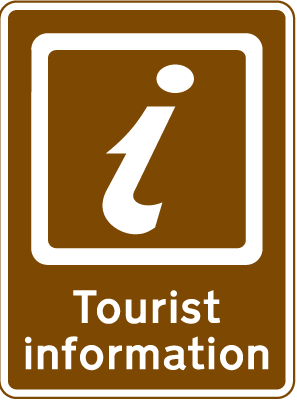
i / Information / Zeichen
ich suche das "i"-Zeichen, wie es für viele Informationsschilder etc. verwendet wird.
Weiß jemand von euch, ob es sich hierbei um einen bestimmten Font bzw. ein Zeichen eines bestimmten Fonts handelt oder ob man das ganze nur als Piktogramm, wie auf dem Bild von Erco, bekommt?
da gibts doch tausende verschiedene versionen.
oder gibt es da eine deutsche, offizielle version?
eigentlich ist das bei jeder größeren clipartbibliothek dabei.
es gibt auch massig dingabtfonts mit diesen zeichen.
leider ist es bei mir nicht in zahlreichen systemfonts drin sondern lediglich in der apple symbols.. aber reicht ja.. :-)
aber es ist nicht genau das was ich suche. wie robertmichael schon meinte, gibt es da wohl tatsächlich etliche versionen, eigentlich hatte ich gedacht, es gibt da ein "offizielles". weiß da jemand was genaueres?
es freut mich ja schon irgendwie, dass es kein "offizielles" gibt oder zumindest nicht soweit bekannt ist, dann darf ich es selbst zeichnen.. :-)
Zeichne das auch (meist) selbst, passend zu den anderen Piktogrammen, die ich so von Arbeit zu Arbeit neu zu entwickeln habe. Immer weiß auf grün, im Tourismusbereich. Und schön fett, aber ohne Serifen ...
das schreit doch nach einer i-Sammlung!